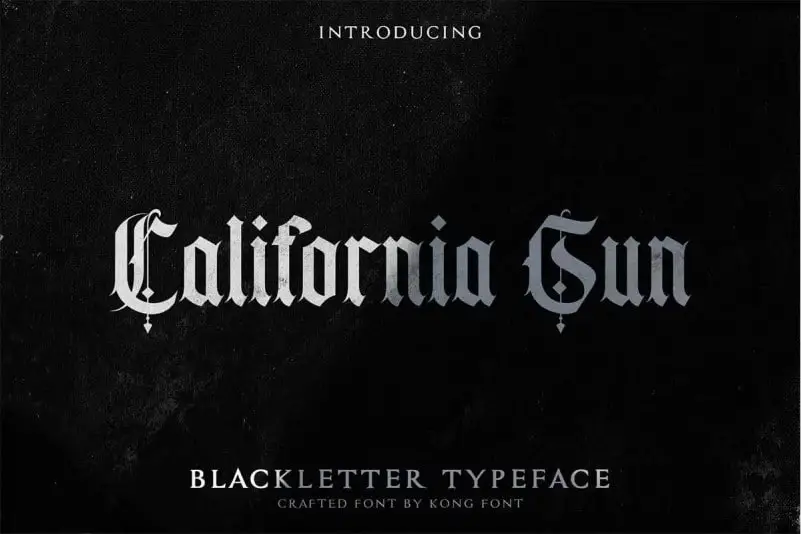
California sun Blackletter Font – Fonte Grátis
California sun Blackletter Font
A California sun Blackletter Font é uma herança do mundo da caligrafia germânica, oferecendo uma aparição elegante e divertida que convida à diversão. Este belo tipo de escrita tem um tom forte que o torna ideal para uso como fonte de exibição, excelente para criar aconchegantes convites para casamentos, aniversários e outros dias especiais. Além disso, este font é uma coleção perfeita de letras e números, adequada para diversos projetos. Perfeito tanto para Logotipos, Design de Marca e criações de Logomarca, também se destaca em Digital Lettering Arts, arte para camisetas ou roupas, cartazes, anúncios em revistas e sinais urbanos. A California sun Blackletter Font é uma escolha incrível para qualquer projeto que exija um estilo único e memorável. Com seu design atraente e versátil, este font certamente trará o toque final perfeito aos seus projetos de design gráfico.